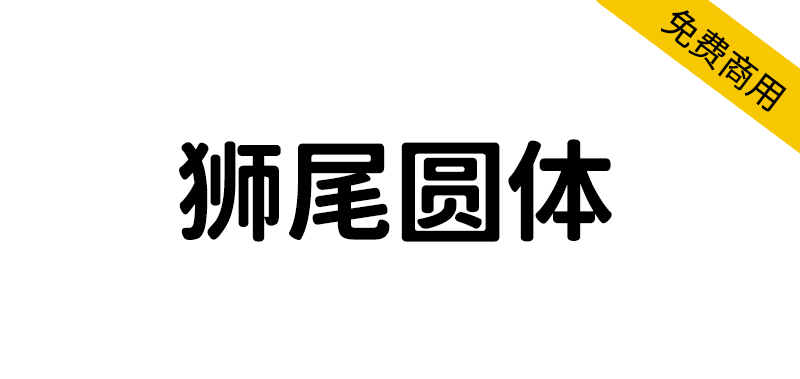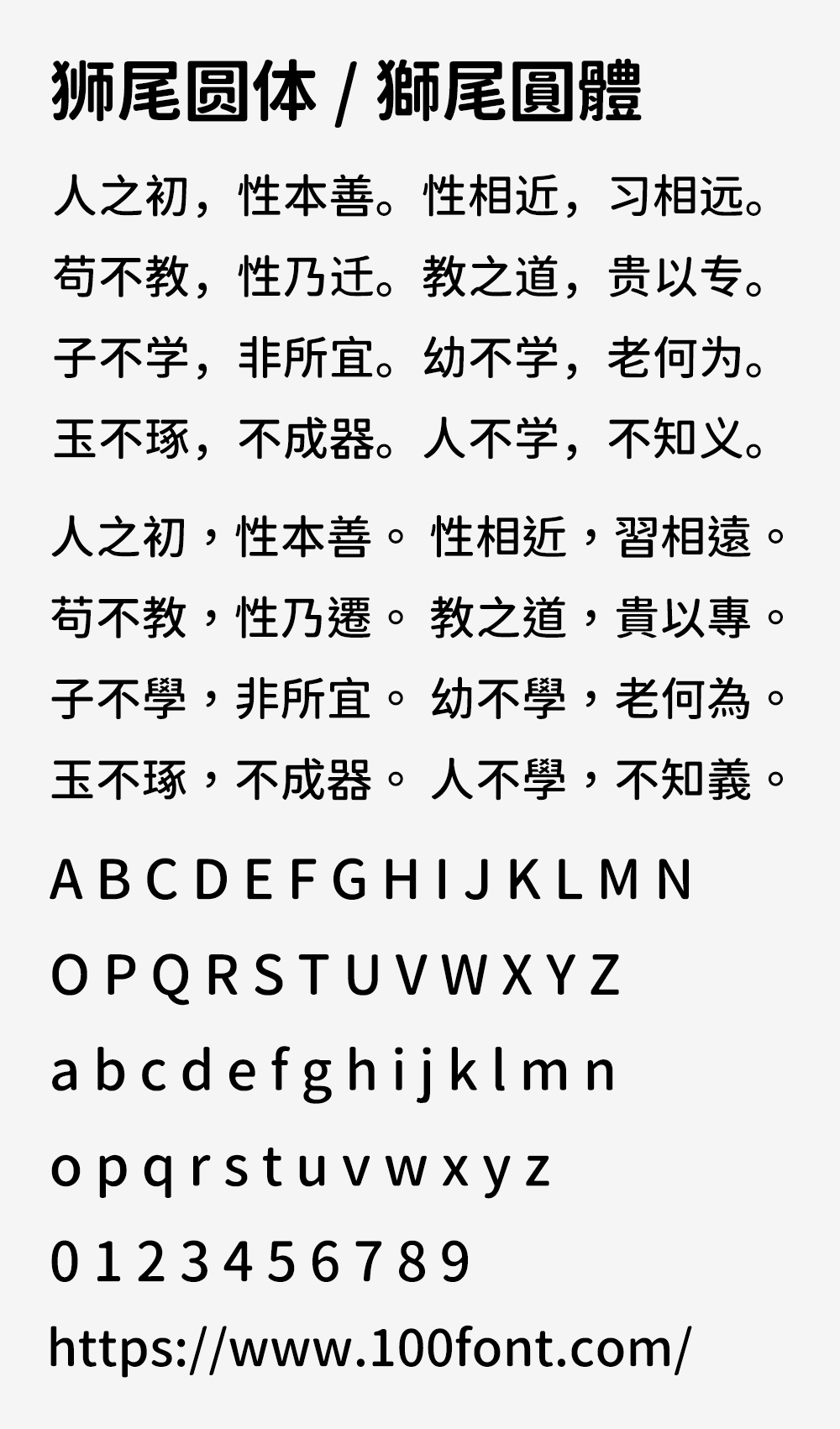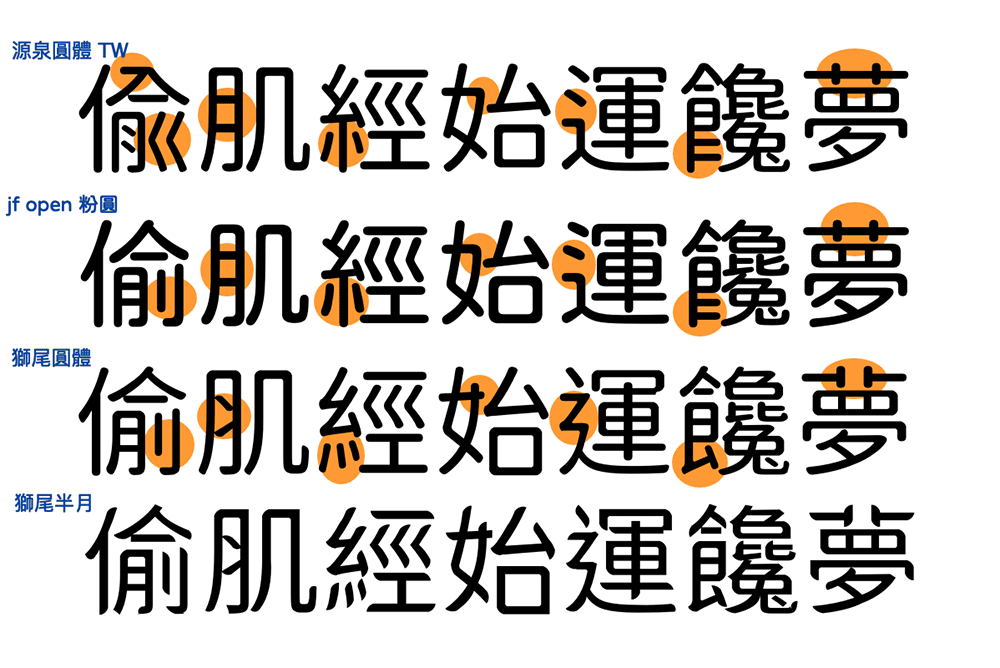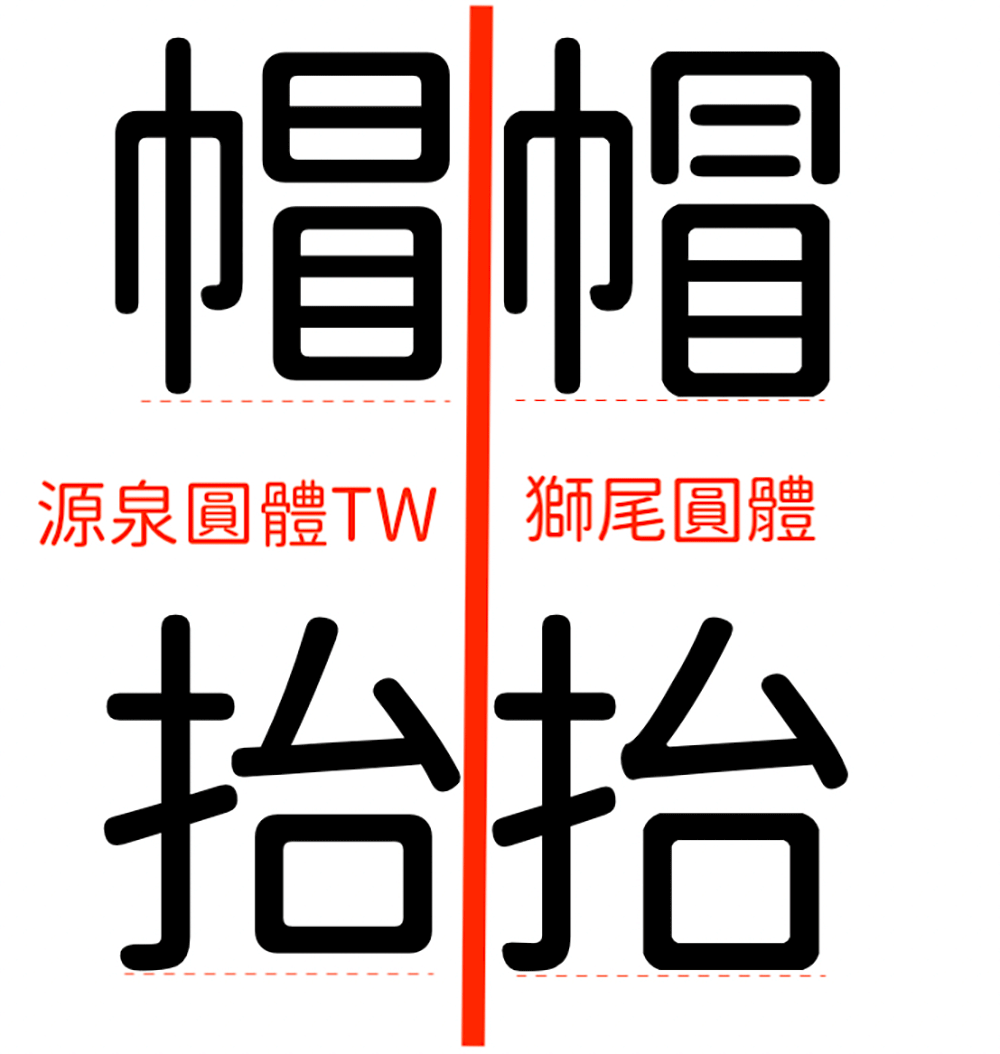
狮尾圆体基于思源黑体的拔脚和加圆改造,更加简明现代化的字体。和思源黑体一样,有7种字重,支持简体中文、繁体中文、韩文与日文。
狮尾圆体和「狮尾腿圆」差别在有没有拔脚,「拔脚」就是会有较少的笔画,例如移除「口」字的左右下角会多出的短线条。有拔脚的字会较圆,但是会造成有些字因直接去掉腿后左右不平衡、左右不对衬的「悬空」问题。改使用「腿」系列字体就不会有这个问题。